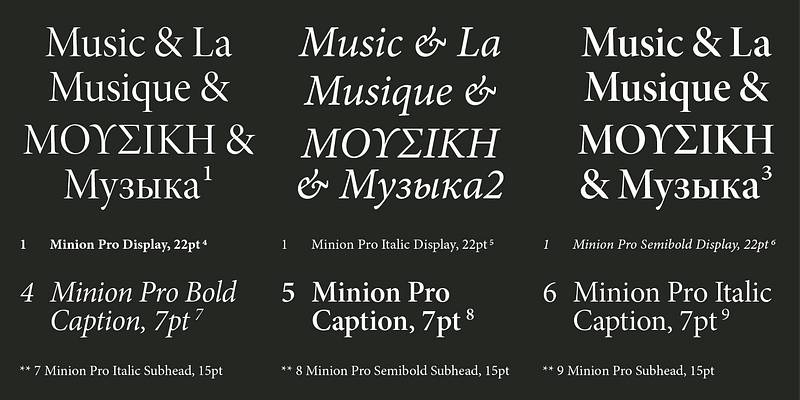
Minion Pro ist eine Adobe Originals-Schriftart, die von Robert Slimbach entworfen wurde. Die erste Version der Minion wurde 1990 vorgestellt. Kyrillische Ergänzungen wurden 1992 veröffentlicht und die OpenType Pro Version erschien schließlich im Jahr 2000. Minion Pro ist von den klassischen Schriften der Spätrenaissance inspiriert, einer Periode eleganter, schöner und gut lesbarer Schrift-Designs. Minion Pro kombiniert die ästhetischen und funktionalen Qualitäten, die Textschriften so gut lesbar machen, mit der Vielseitigkeit der digitalen OpenType-Technologie. Das Ergebnis ist eine noch nie dagewesene Flexibilität und typografische Kontrolle, sei es für längere Texte oder für Display-Anwendungsfälle. Die komplette Minion Pro-Familie umfasst drei Schriftstärken und zwei Breiten, jeweils mit optischen Größenvarianten, und unterstützt eine ganze Reihe westlicher Sprachen, einschließlich Griechisch und Kyrillisch. Mit ihren zahlreichen Ligaturen, Kapitälchen, Mediävalziffern, Zierbuchstaben und anderen zusätzlichen Glyphen ist die Minion Pro ideal für den Einsatz bei Büchern in limitierter Auflage, Newslettern und Verpackungen.